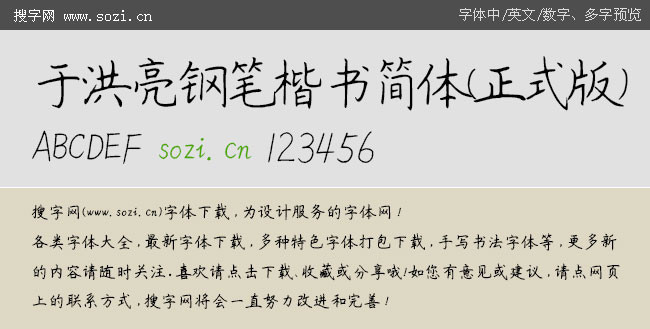
于洪亮鋼筆楷書簡體(正式版)
搜字網(wǎng)提供一款于洪亮鋼筆楷書簡體(正式版)中文書法字體下載,于洪亮硬筆行楷手寫體正式版是一款手寫風(fēng)格的鋼筆書法字體,字體書寫流暢,字形大方,整體效果十分出色,適合應(yīng)用于廣告設(shè)計、名片設(shè)計、包裝印刷、產(chǎn)品設(shè)計等應(yīng)用。